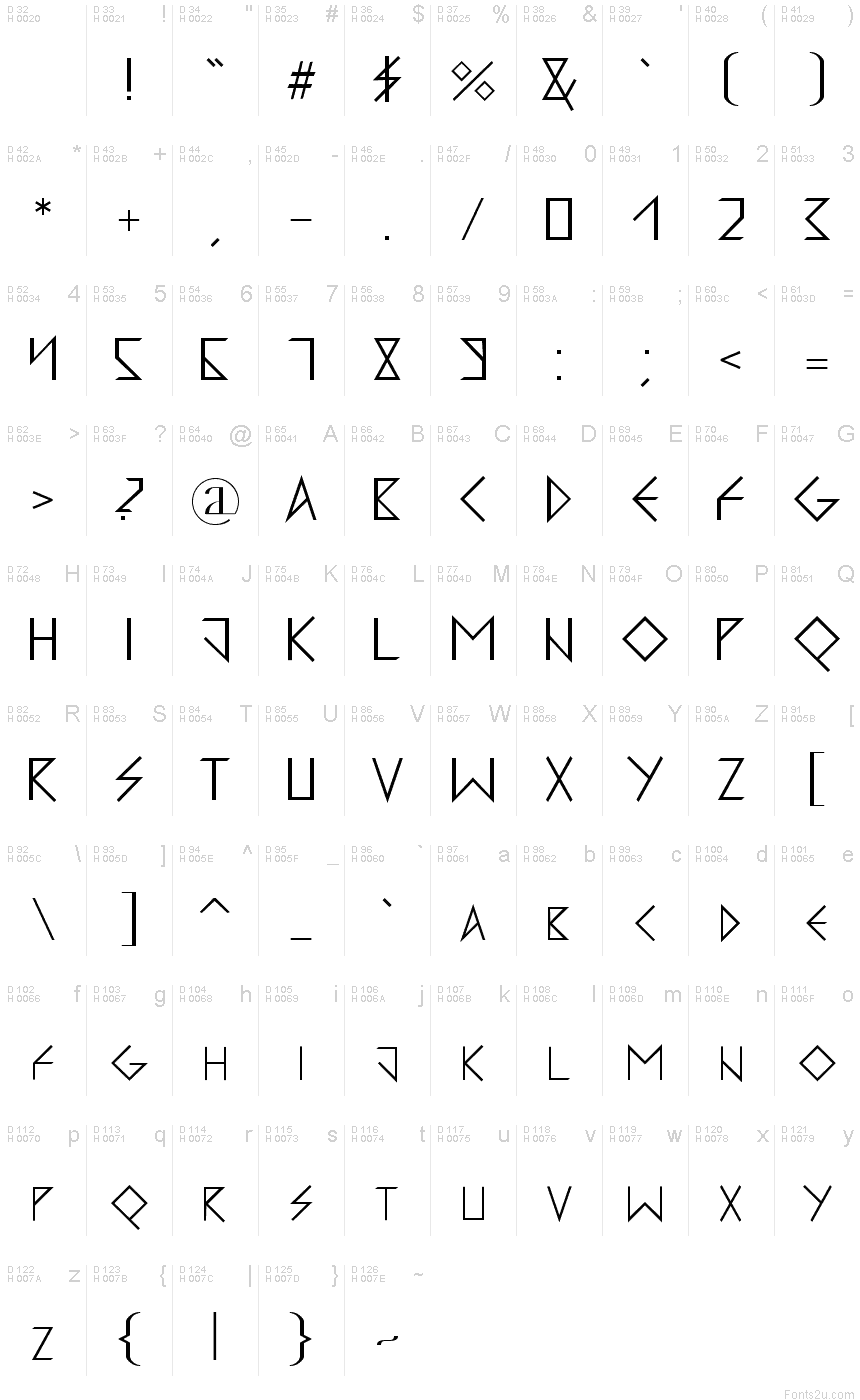
Ivan autorstwa Nikoli Kovanovica to bezpłatny, geometryczny krój typu display o chłodnym, minimalistycznym i modernistycznym charakterze. Litery oparto na ostrych przekątnych i smukłych pionowych liniach, a dzielona, trójkątna litera A nadaje całemu projektowi lekko eksperymentalny sznyt, nie naruszając jego przejrzystego rytmu.
Świetnie sprawdza się na plakatach, w identyfikacji wizualnej galerii, na okładkach płyt, w tytułach oraz w brandingu modowym, gdzie kilka znaków musi nadać ton. Jako darmowy font, IVAN doskonale pasuje do krótkich nagłówków, monogramów i okładek, ponieważ jego wąska struktura i ostre kąty tworzą wyrazistą, graficzną sylwetkę nawet w bardzo krótkich tekstach.